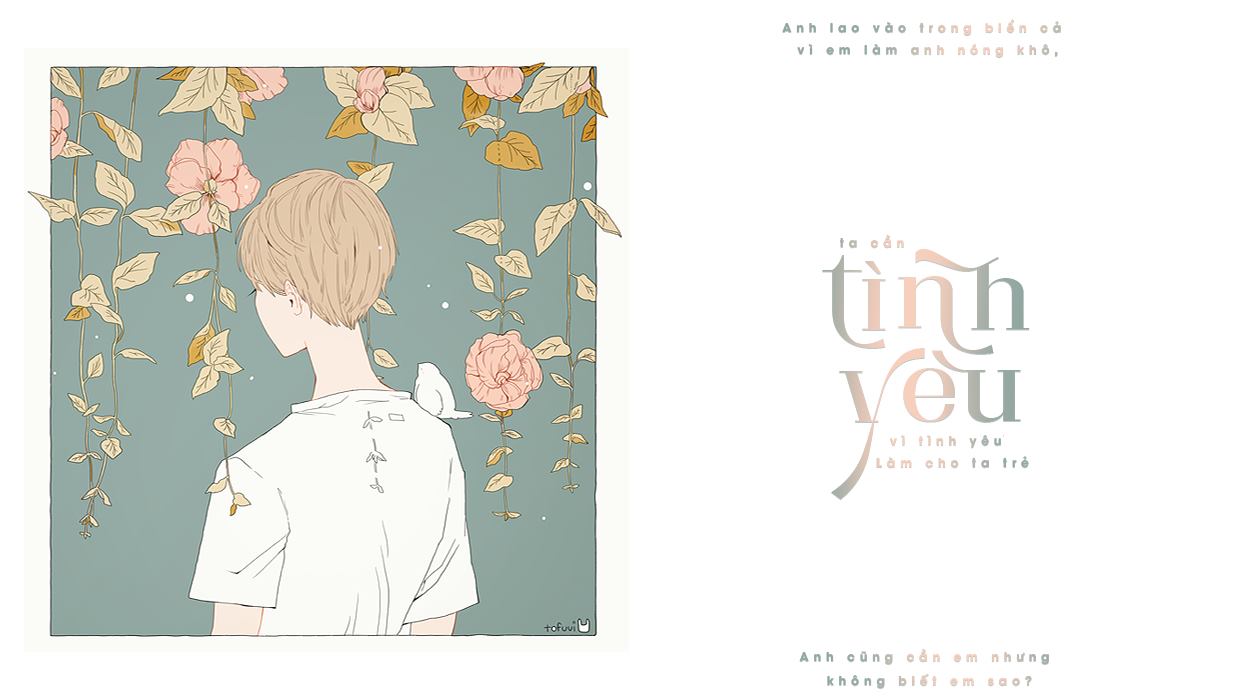
Giới thiệu font Matterdi, một dòng serif thời trang cao cấp thanh lịch với rất nhiều chữ ghép độc đáo và thời trang. Bộ font Matterdi Việt Hóa bao gồm 11 font đầy đủ.
Font Matterdi Việt Hóa chứa hơn 100 chữ ghép và chữ thay thế độc đáo, thanh lịch. 9 weight có sẵn từ Thin đến Black cho bạn nhiều khả năng bố trí các dự án tiếp theo của mình.
Hãy thử Matterdi Bold cho tiêu đề hiển thị hoặc Matterdi Thin để có giao diện thời trang và thanh lịch. Nó cũng hoàn hảo để ghép nối với một thiết kế dạng vẽ tay!